一、篆书:
它包括商周的甲骨文、金文、春秋战国文字、秦小篆。早期的文字是甲骨文和金文(即钟鼎文)。后来还出现了籀文和石鼓文。以上早期文字通称大篆。秦始皇统一中国以后,所统一的文字,称为小篆。
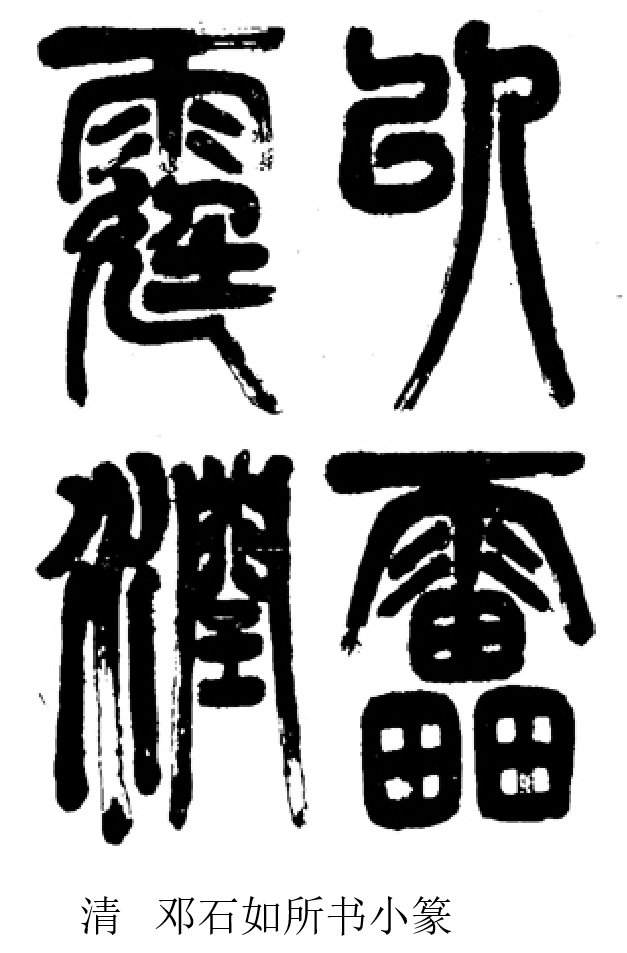
二、隶书:
隶书的出现,是为了加快书写的速度。是汉字一种比较简便易于书写的字体。它出现于秦代,大量使用于汉代。隶书将篆书的笔画减少,将圆匀的线条截断,化圆为方,变弧线为直线。
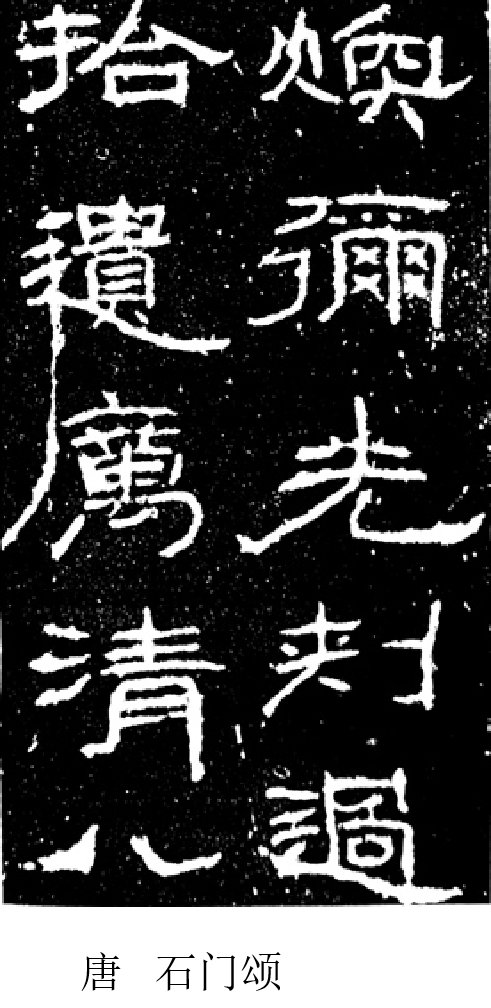
又称“真书”“正书”、“正楷”。楷是法式之意。楷书萌芽于西汉,魏晋以后盛行。楷书是隶书的定型化,它把隶书的波势挑法变得平稳,把隶书的慢弯变成了硬勾,把隶书的平直方正变成了长方形,成为直到现在都十分通行的字体。
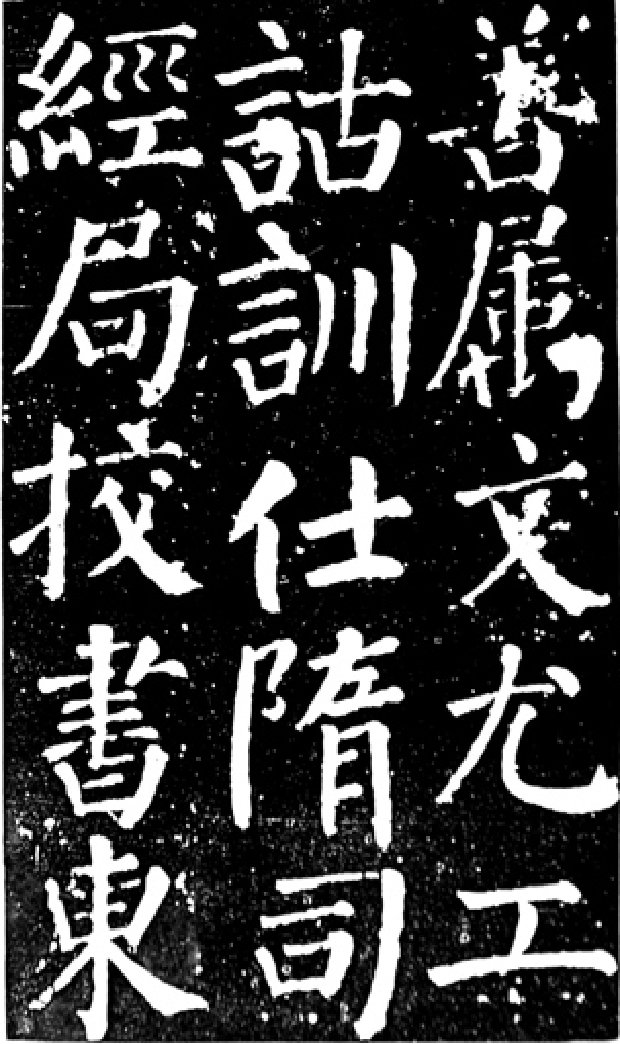
草书:
草书是为了适应快速书写的要求而出现的。草书作为一种字体而正式具有其名,还是东汉章帝时的事。章草保持有隶书的笔势,比隶书简易,有些点画有所省略。
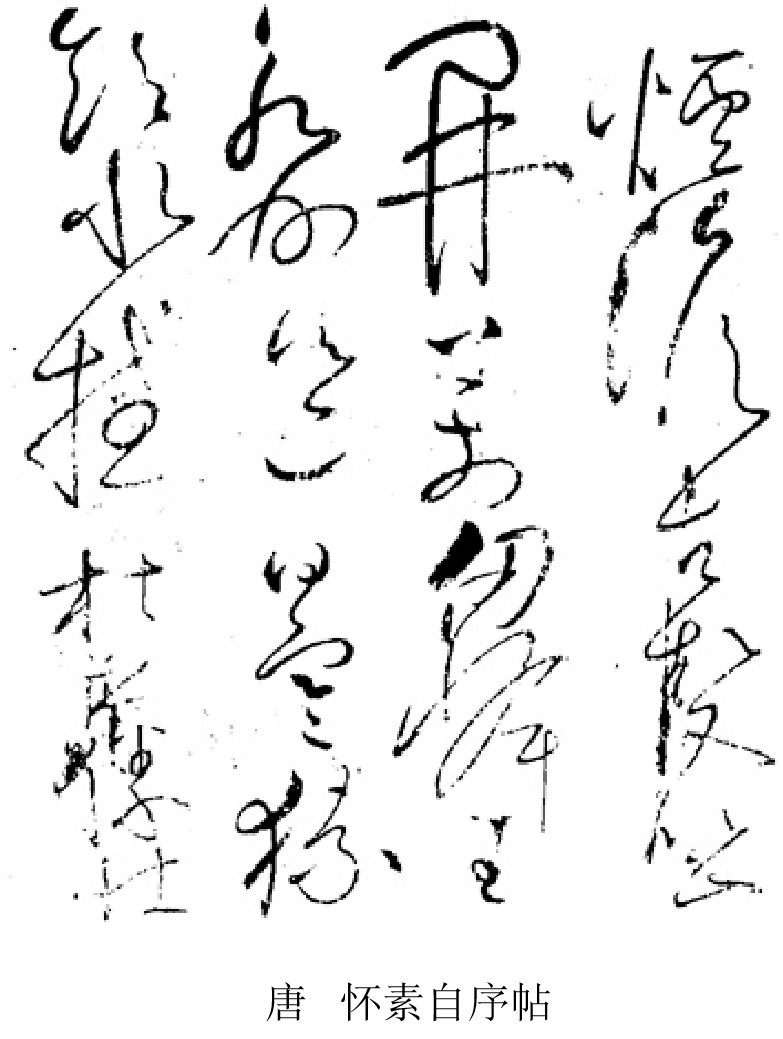
行书
行书兴起于东汉,是介乎草书和楷书之间的一种字体,它的书写速度比楷书快,但又不像草书那样难以辨识,兼有楷书字形易识、草书书写快捷之长。